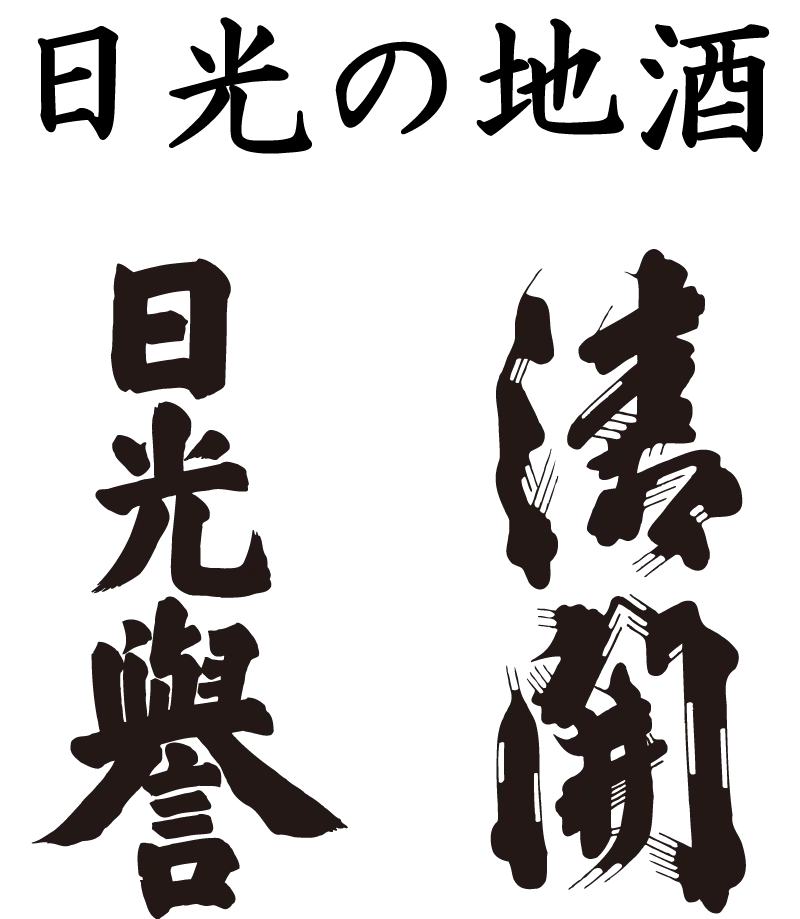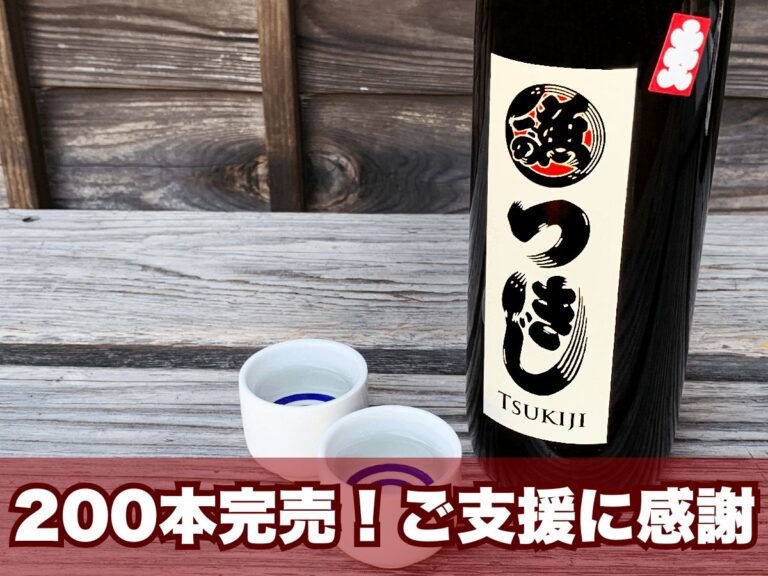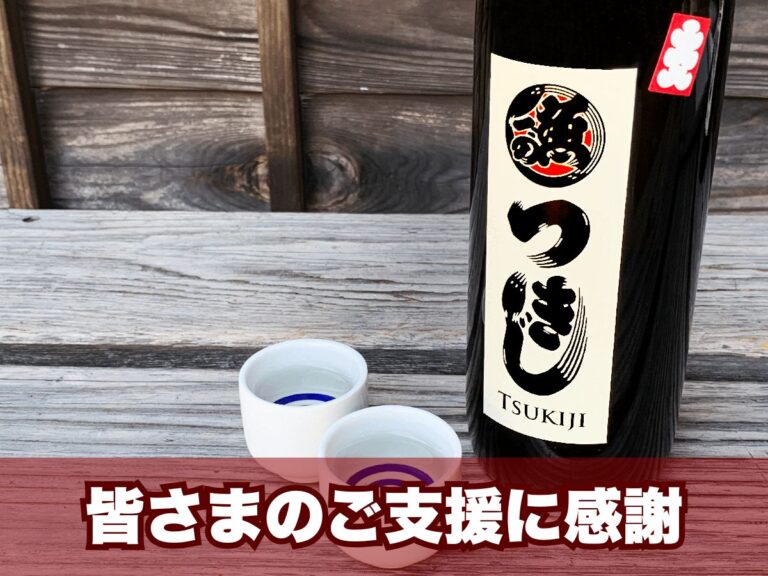
伝統の江戸文字
感じる築地の歴史
「つきじ江戸文字と歴史伝承の会」は、商売繁盛を意味する「江戸文字」と
その文字と共に歴史を刻んだ「築地」を次世代に伝承するNPO法人です。
私たちは、江戸文字体験会を通じて、手書きの素晴らしさと築地の歴史の深みを紹介して、日本の伝統を守り育てています。
文字と歴史に触れ、新たな発見と感動を共有できれば幸いです。